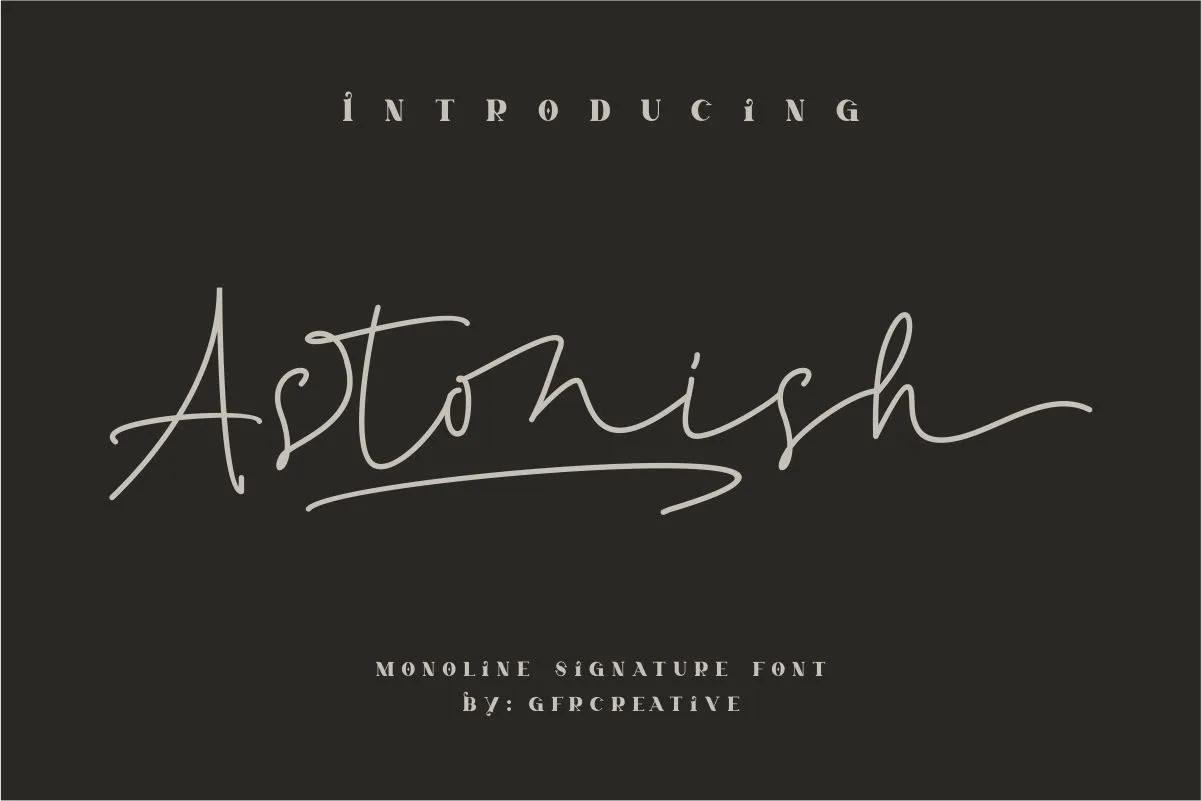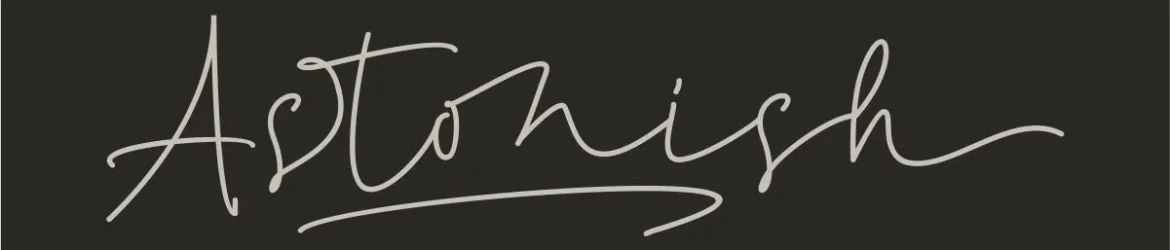
A Astonish Font é uma elegante e sofisticada tipografia script monolínea que oferece um toque handwritten perfeito para projetos incríveis. Com linhas finas e formas sutis, esta fonte é ideal para aqueles buscando dar um toque delicado a qualquer projeto, seja em cartazes de eventos, logotipos ou materiais digitais. Suave e arrojada ao mesmo tempo, Astonish é uma escolha perfeita tanto para ambientes formais quanto para atmosferas mais descontraídas. Compreender o potencial desta fonte é como receber um presente de arte digital, que adicionará um toque único a qualquer design.